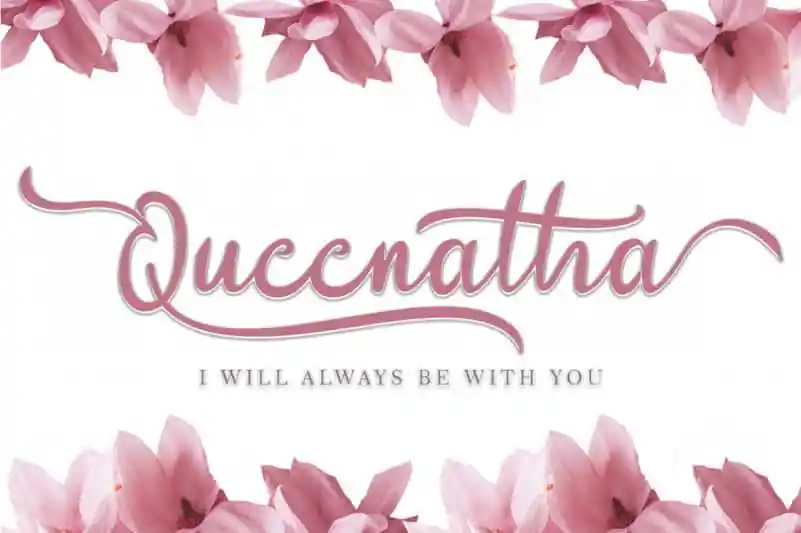
Queenatha Calligraphy Font – Download Grátis
A Queenatha Calligraphy Font é uma elegante escolha para designers que desejam dar um toque refinado a qualquer projeto. Suavemente encantadora e versátil, ela se destaca não apenas para trabalhos relacionados à cerimônias de casamento, mas também para momentos de descanso no turismo ou entretenimento. Seja uma agenda da viagem ou uma estampa de status em redes sociais, a Queenatha oferece um toque sofisticado que torna qualquer projeto mais especial e memorável. Além disso, ela é perfeita para criar logotipos, marcas e tudo o que está relacionado ao branding do seu negócio. Para quem busca uma fonte que não apenas deixa sua marca, mas acentua cada frase com delicadeza, a Queenatha Calligraphy Font é sem dúvida um investimento valioso.